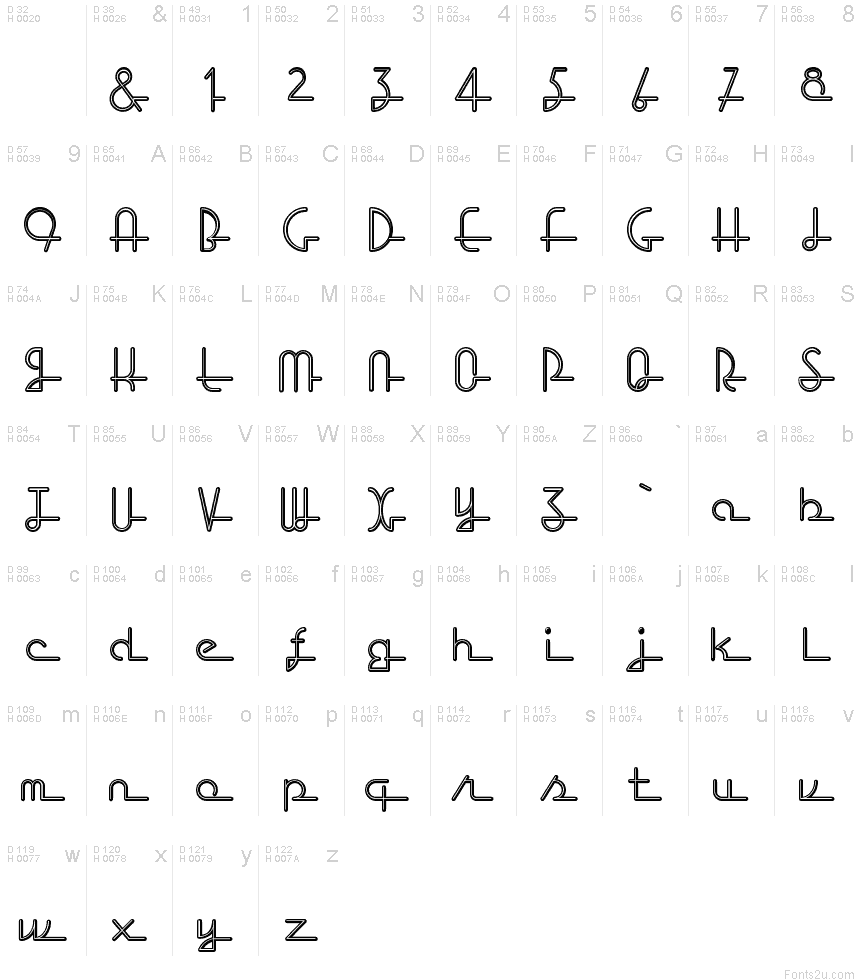
Lost Wages autorstwa Nicka Curtisa to darmowy, utrzymany w stylistyce groovy krój typu display. Posiada obrysowane, zaokrąglone formy oraz ciągłą linię bazową, dzięki której litery zdają się płynnie przechodzić jedna w drugą. Mieszanka długich pionowych kresek, zapętlonych krzywizn i ciasnych połączeń nadaje całości odręczny, plakatowy rytm, który nie wygląda przy tym chaotycznie.
Ten darmowy font świetnie sprawdza się w nagłówkach, ulotkach imprezowych, okładkach albumów, logotypach i grafikach z cytatami, gdzie to sam krój musi nieść przekaz. Lost Wages pasuje również do szyldów, brandingu i składu redakcyjnego, ponieważ jej połączone kreski oraz zwarta, falista struktura przyciągają wzrok już przy kilku słowach.